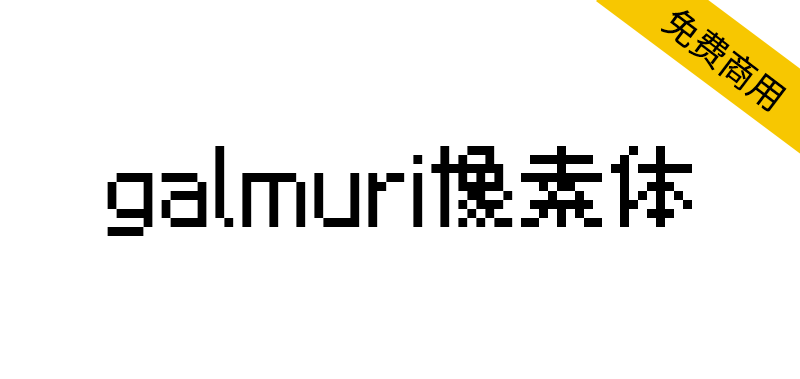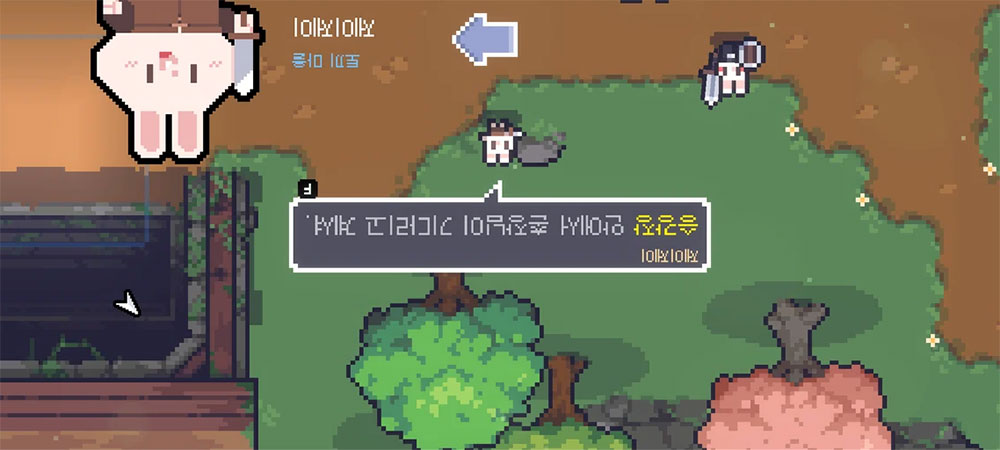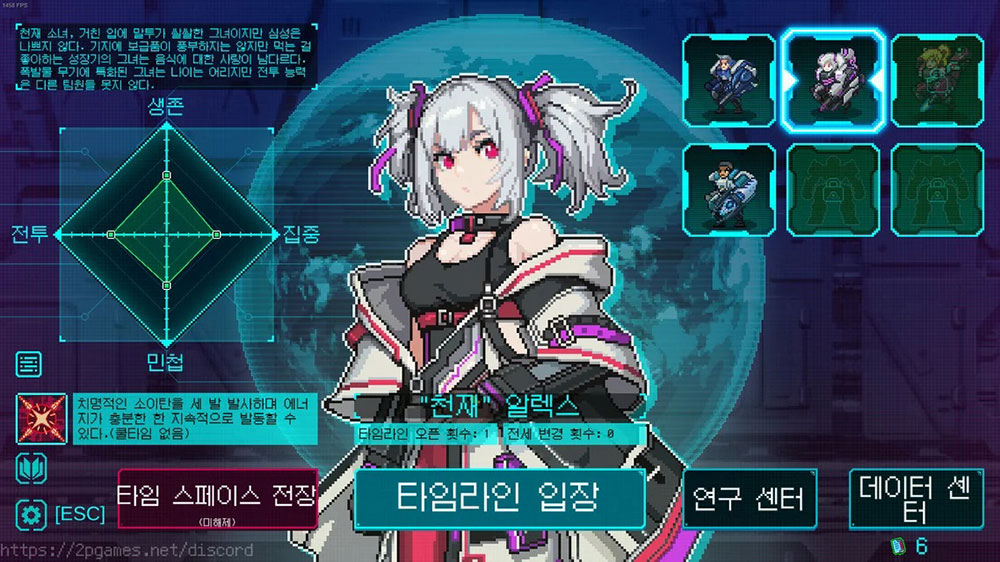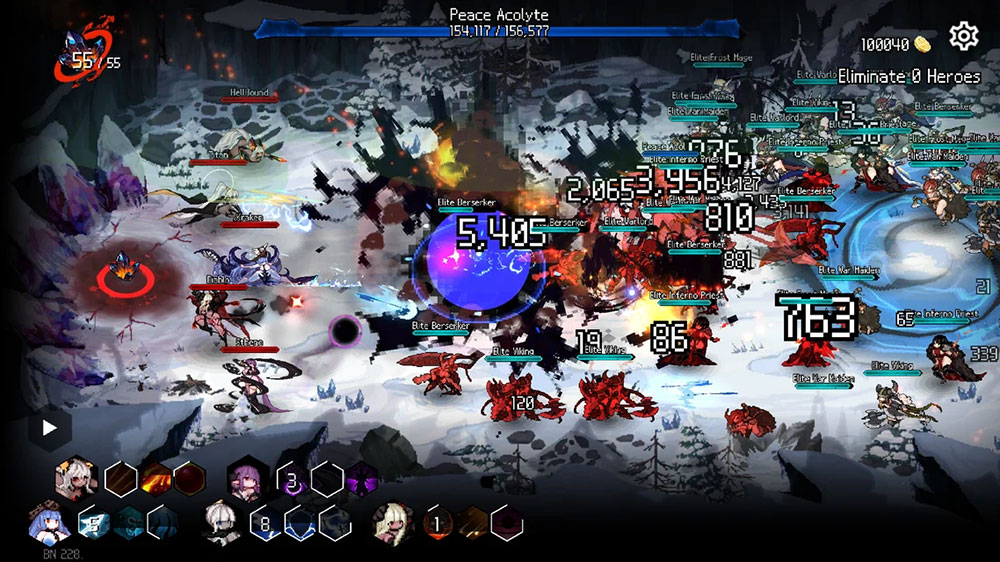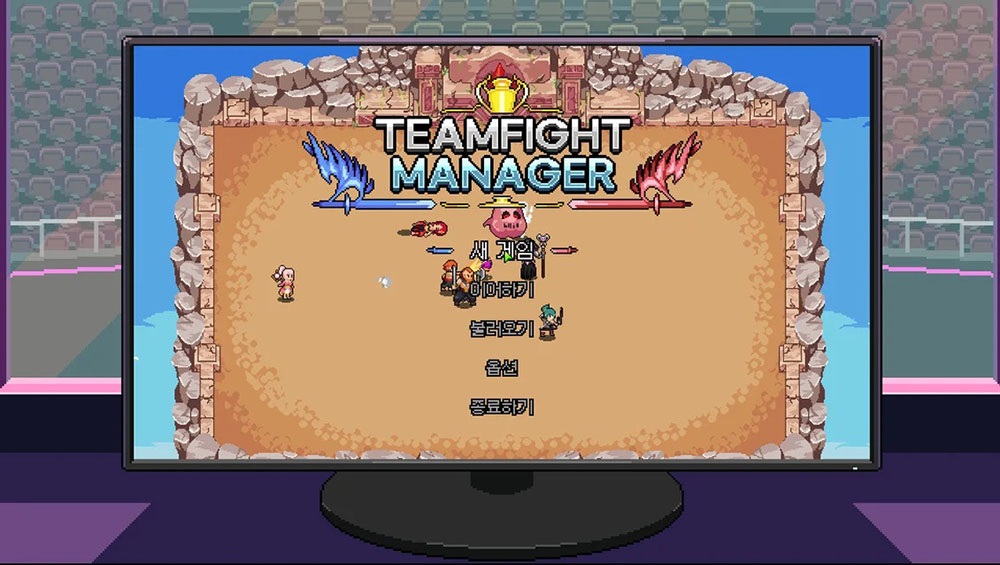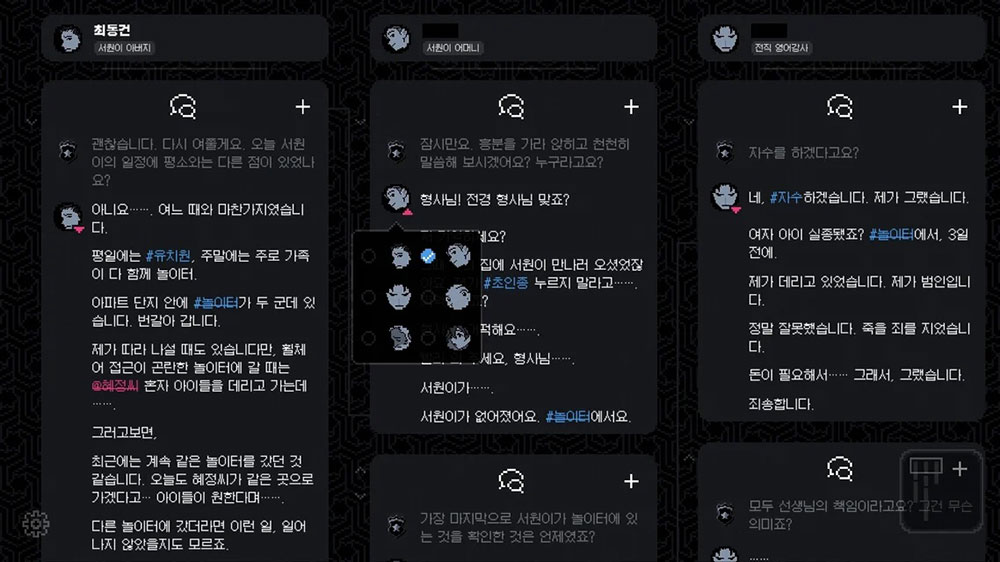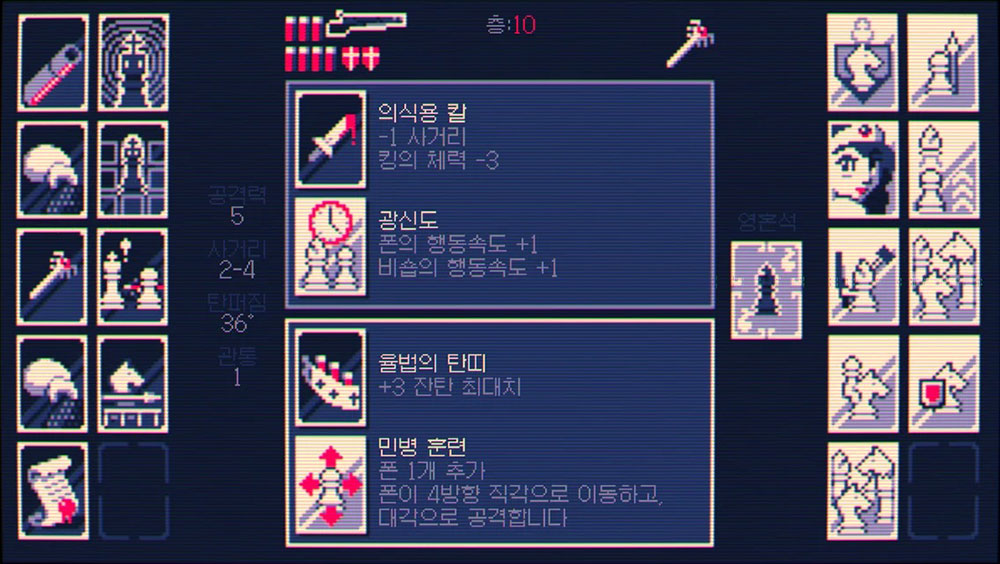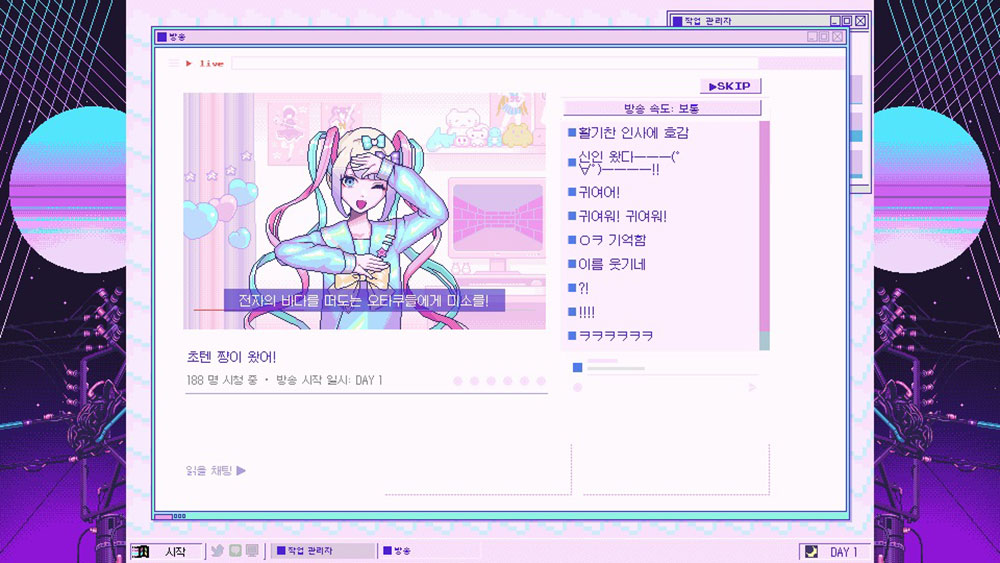
Galmuri 是一款在小字号下仍保持良好可读性与平衡性的韩文点阵字体,受任天堂DS主机及游戏软件所用字体设计启发而创作。该字体于2019年10月9日韩文日首次公开发布,其名称"Galmuri"源自2008年6月由韩语本地化社区"한식구"成员金东翰(Kim Donghan)制作发布的点阵字体"갈무리M"。(若需在日语环境下使用,推荐选用GalmuriMono版本,该版本中波浪号等符号为全角格式)
Galmuri14 在 15px (11pt) 时最清晰,Galmuri11 在 12px (9pt) 时最清晰,Galmuri9 在 10px (7.5pt) 时最清晰,而 Galmuri7 在 8px (6pt) 大小和倍数时最清晰。
Galmuri는 닌텐도 DS 본체와 소프트웨어에 사용되었던 폰트 디자인에서 영감을 받은 비트맵 폰트입니다. 작은 크기에서도 가독성 좋고 균형 있는한글 비트맵 폰트.2019년 10월 9일 한글날에 처음 공개되었으며, Galmuri의 이름은 2008년 6월 사용자 한글화 커뮤니티 한식구에서 김동한 님께서 만들어 배포하신 비트맵 폰트 갈무리M에서 유래하였습니다.일본어 환경에서 사용할 경우 낫표 등이 전각으로 되어 있는 GalmuriMono를 권장합니다.
Galmuri14는 15px (11pt), Galmuri11은 12px (9pt), Galmuri9는 10px (7.5pt), Galmuri7은 8px (6pt) 크기와 그 배수에서 가장 명확하게 표시됩니다.